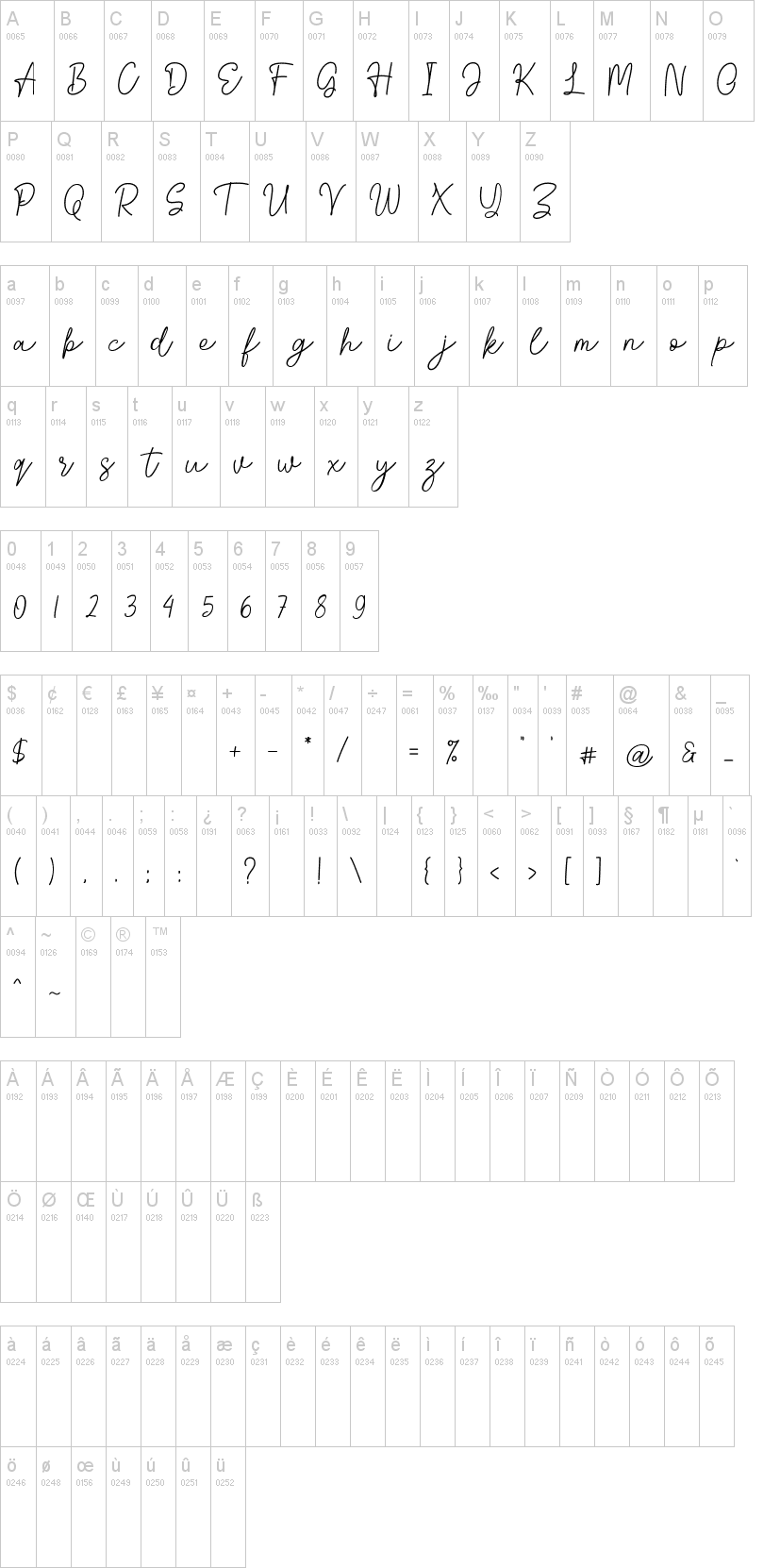
Talliya
Talliya 是一款字体,它具有优雅的外观和精致的细节。它的字母形状是温柔的,有着清晰的轮廓,而且每个字母都有一个特殊的结构,使其具有自然而又独特的风格。Talliya 字体由设计师精心调制,可用于多种用途,如印刷、网页设计、海报设计等。Talliya 字体有着独特的外观,可以为您的设计添加一份特别的气质,让您的作品更加出彩。
Talliya是一款非常不错的手写艺术字体,具有很好的视觉感,适合于文化类的宣传设计、商业类品牌的广告和产品包装设计以及个性化文字排版等较多场景。